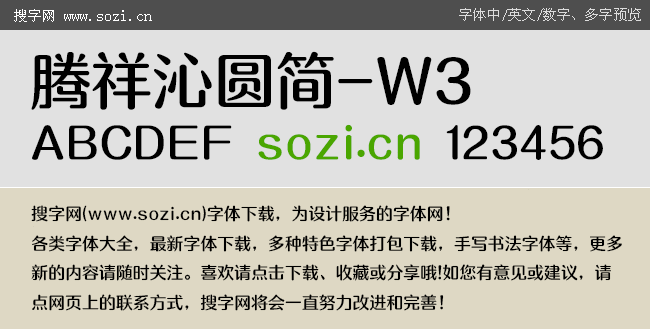
騰祥沁圓簡-W3
搜字網(wǎng)提供一款騰祥沁圓簡-W3中文藝術(shù)字體下載,騰祥沁圓簡-w3是一款應(yīng)用于廣告創(chuàng)意設(shè)計方面的中文簡體字體,該字體線條粗細(xì)適中,字形端正大方得體,整體效果非常的出眾,可以應(yīng)用于橫幅標(biāo)語、美術(shù)設(shè)計、宣傳海報、圖形設(shè)計等領(lǐng)域。